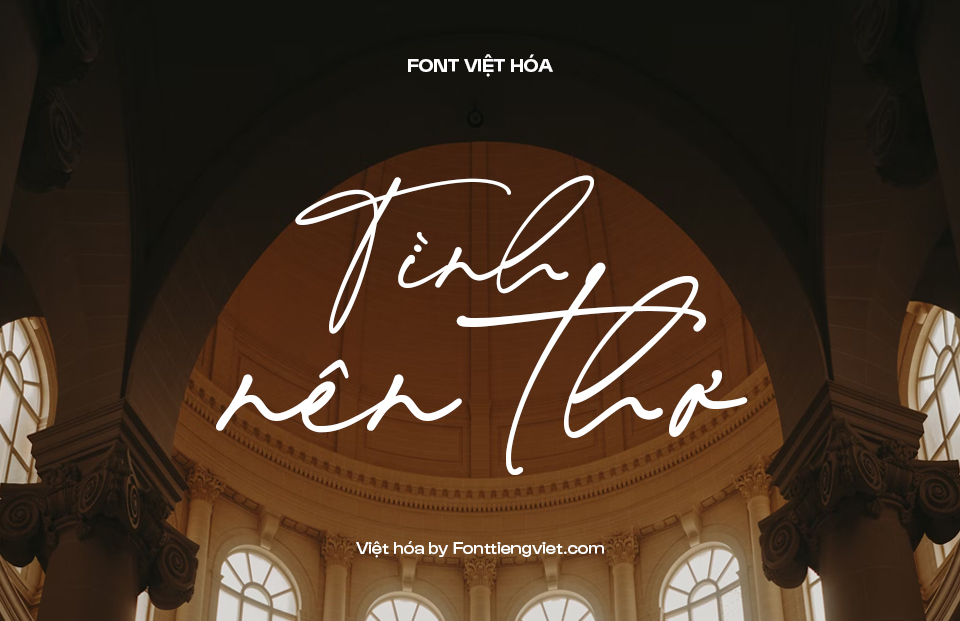
Tiêu điểm thiết kế: Đánh giá chi tiết Font Việt hóa 1FTV Woodsen Signature
Trong thế giới thiết kế đồ họa hiện đại, việc lựa chọn Font Chữ phù hợp đóng vai trò then chốt trong việc truyền tải thông điệp và cảm xúc. Đặc biệt, đối với các nhà thiết kế, giáo viên, và học sinh – sinh viên đang tìm kiếm sự độc đáo cho các dự án cá nhân hoặc luận văn tốt nghiệp, một font chữ ký (signature font) mang tính thẩm mỹ cao luôn là ưu tiên hàng đầu. Hôm nay, chúng ta sẽ đi sâu vào tìm hiểu về Font Việt hóa 1FTV Woodsen Signature, một lựa chọn tuyệt vời đã được tối ưu hóa để sử dụng hoàn hảo trong ngôn ngữ tiếng Việt. Đây không chỉ là một phông chữ đẹp mà còn là công cụ mạnh mẽ giúp nâng tầm mọi ấn phẩm.
Font Việt hóa 1FTV Woodsen Signature – Nét tinh tế cho mọi dự án
Woodsen Signature là một kiểu chữ script độc đáo, mô phỏng chân thực nét viết tay mềm mại, tự nhiên và đầy cá tính. Phong cách này thường được các thương hiệu cao cấp, các nhà sáng tạo nội dung, và đặc biệt là sinh viên sử dụng trong các ấn phẩm mang tính cá nhân hóa cao. Phiên bản 1FTV Woodsen Signature được cộng đồng thiết kế đánh giá cao nhờ vào sự kết hợp hài hòa giữa tính nghệ thuật và độ dễ đọc. Khi nhắc đến phông chữ ký, yếu tố Việt hóa trở nên vô cùng quan trọng, đảm bảo rằng tất cả các dấu thanh, chữ cái đặc biệt của tiếng Việt đều được hiển thị một cách chính xác và mượt mà, giữ nguyên tinh thần thiết kế ban đầu. Sự tỉ mỉ trong quá trình Việt hóa đã biến Font Việt hóa 1FTV Woodsen Signature thành một tài sản không thể thiếu cho các dự án tại Việt Nam.
Phong cách chữ ký độc đáo
Điểm mạnh lớn nhất của Woodsen Signature chính là cảm giác chân thật như được viết bằng bút mực. Những đường cong uyển chuyển, độ dày mỏng linh hoạt của nét chữ tạo nên sự sang trọng, rất phù hợp cho việc thiết kế logo, thiệp mời, tiêu đề các bài thuyết trình quan trọng, hoặc các tài liệu học tập yêu cầu tính nghệ thuật cao. Đối với học sinh cấp 3 chuẩn bị cho các dự án cuối năm hay bài tập lớn, việc sử dụng font chữ ký này có thể giúp bài làm của họ nổi bật hơn hẳn so với các font thông thường khác. Nó thể hiện sự đầu tư nghiêm túc và gu thẩm mỹ tinh tế của người tạo ra ấn phẩm.
Ứng dụng của Font Woodsen trong môi trường học thuật và sáng tạo
Mặc dù là font chữ ký, 1FTV Woodsen Signature vẫn có phạm vi ứng dụng rộng lớn, đặc biệt là trong bối cảnh giáo dục và các kỳ thi tốt nghiệp. Các dự án học thuật không chỉ cần sự chính xác về mặt nội dung mà còn cần tính hấp dẫn về mặt hình thức. Font chữ này cung cấp giải pháp hoàn hảo cho những nhu cầu đó.
- Thiết kế dự án và luận văn tốt nghiệp: Sinh viên có thể dùng Woodsen Signature cho các tiêu đề chính, tên chương, hoặc chữ ký điện tử trên bìa luận văn. Điều này tạo ra một ấn tượng chuyên nghiệp, khác biệt ngay từ cái nhìn đầu tiên.
- Tạo ấn phẩm kỷ niệm và bằng khen: Các trường học thường xuyên cần thiết kế các loại chứng nhận, bằng khen, hoặc thư chúc mừng. Việc sử dụng Woodsen Signature mang lại sự trang trọng, cá nhân hóa cao, giúp nâng cao giá trị của văn bằng được trao.
- Tài liệu giảng dạy sáng tạo: Giáo viên có thể sử dụng font này để tạo ra các tiêu đề bài giảng thu hút, giúp kích thích sự hứng thú học tập của học sinh. Sự kết hợp giữa nội dung học tập nghiêm túc và hình thức trình bày nghệ thuật là chìa khóa để giữ chân người học.
Việc sử dụng các font chữ độc đáo như Woodsen giúp người dùng thể hiện cá tính mạnh mẽ trong các bài trình chiếu và các dự án thiết kế đồ họa. Đây là một lợi thế cạnh tranh quan trọng cho bất kỳ ai hoạt động trong lĩnh vực sáng tạo hoặc đang theo đuổi các ngành nghề liên quan đến truyền thông và mỹ thuật.
Những lợi ích khác của Font Việt hóa 1FTV Woodsen Signature
Ngoài vẻ đẹp thẩm mỹ, quá trình Việt hóa chuyên nghiệp của 1FTV mang lại sự tiện lợi tối đa cho người dùng. Người dùng không cần phải lo lắng về lỗi font, lỗi dấu hay sự thiếu hụt các ký tự tiếng Việt. Điều này đặc biệt quan trọng khi sinh viên đang gấp rút hoàn thành bài tập hay giáo viên cần chuẩn bị tài liệu gấp. Sự ổn định và tương thích cao của phiên bản Việt hóa là một điểm cộng lớn, giúp tiết kiệm thời gian chỉnh sửa và đảm bảo chất lượng hình ảnh cuối cùng.
Thêm vào đó, các font chữ ký như Woodsen Signature thường yêu cầu kỹ thuật xử lý phức tạp để các nét chữ kết nối mượt mà (ligatures). Phiên bản Việt hóa đã giải quyết triệt để vấn đề này, đảm bảo rằng ngay cả những chuỗi ký tự tiếng Việt phức tạp nhất cũng được hiển thị trôi chảy, không bị gián đoạn. Đây là yếu tố then chốt tạo nên tính chuyên nghiệp và sự khác biệt rõ rệt so với các phiên bản font chữ nước ngoài chưa được tối ưu cho tiếng Việt.
Chúng ta cần nhấn mạnh rằng việc sử dụng font chữ đẹp và chuẩn SEO không chỉ phục vụ mục đích thiết kế mà còn cải thiện trải nghiệm đọc. Đối với các tài liệu trực tuyến, việc chọn font dễ đọc nhưng vẫn độc đáo như Woodsen Signature giúp thu hút và giữ chân người đọc lâu hơn, đặc biệt trong các bài viết blog về giáo dục, thiết kế, hay các thông báo quan trọng từ nhà trường.
Tóm lại, Font Việt hóa 1FTV Woodsen Signature là sự lựa chọn hàng đầu cho những ai tìm kiếm một font chữ ký chất lượng cao, đã được tối ưu hoàn toàn cho tiếng Việt. Từ các dự án học tập nhỏ của học sinh cấp 3, cho đến các luận văn tốt nghiệp mang tính học thuật, hay các ấn phẩm thương hiệu chuyên nghiệp, Woodsen Signature đều mang lại giá trị vượt trội. Đừng ngần ngại sử dụng font chữ này để tạo nên sự khác biệt và đẳng cấp cho tác phẩm của bạn. Việc đầu tư vào chất lượng hình ảnh thông qua font chữ chính là đầu tư vào uy tín và sự chuyên nghiệp của bản thân. Hãy khám phá và ứng dụng ngay Font Chữ tuyệt vời này vào công việc và học tập hàng ngày của bạn!